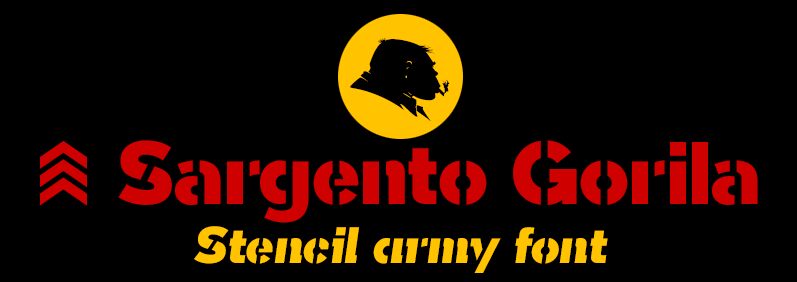
Użyj ligatur:
Dwa symbole Bitcoina: (b#, B#)
Symbol sierżanta: #, a#
Sargento Gorila: SGT
Wersja komercyjna zawiera alfabet cyrylicy i zestaw Latin Extended-A, liczne symbole walut, alternatywne znaki oraz różne ligatury.
Sargento Gorilla is a sans stencil type military style that includes the Cyrillic alphabet, several monetary symbols including Bitcoin, alternative letters and various ligatures. Created in 2017 and based on my previous typography Tabarra Sans Black.